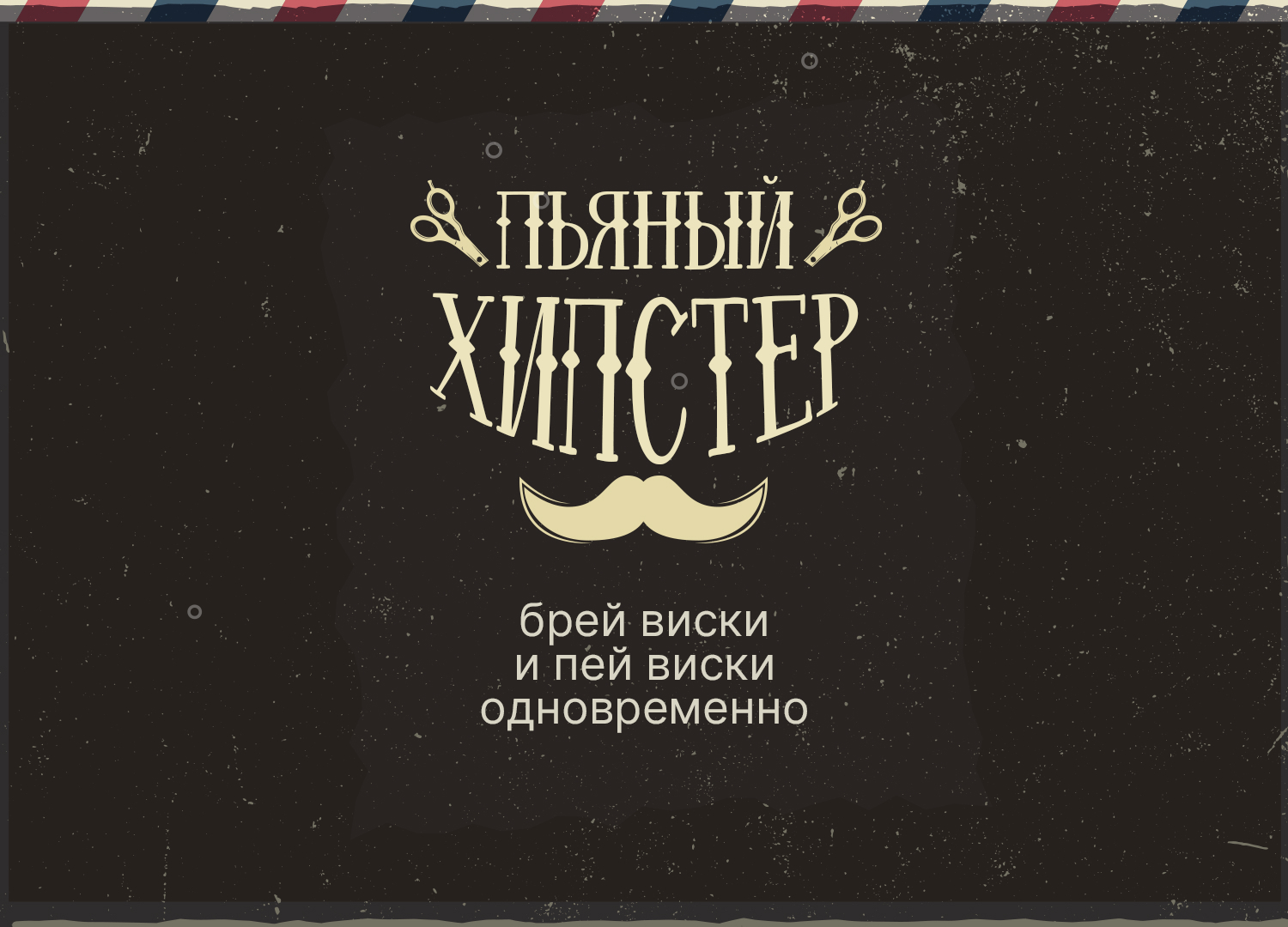
Бесплатный шрифт charming
🤘Новая презентация. Декоративный шрифт, отлично впишется под байкерские, барберные, винтажные и хипстерские темки. Читаемость для коротких заголовков.